今回は、CEES W. DE JONG著、『SANS SERIF』を紹介します。
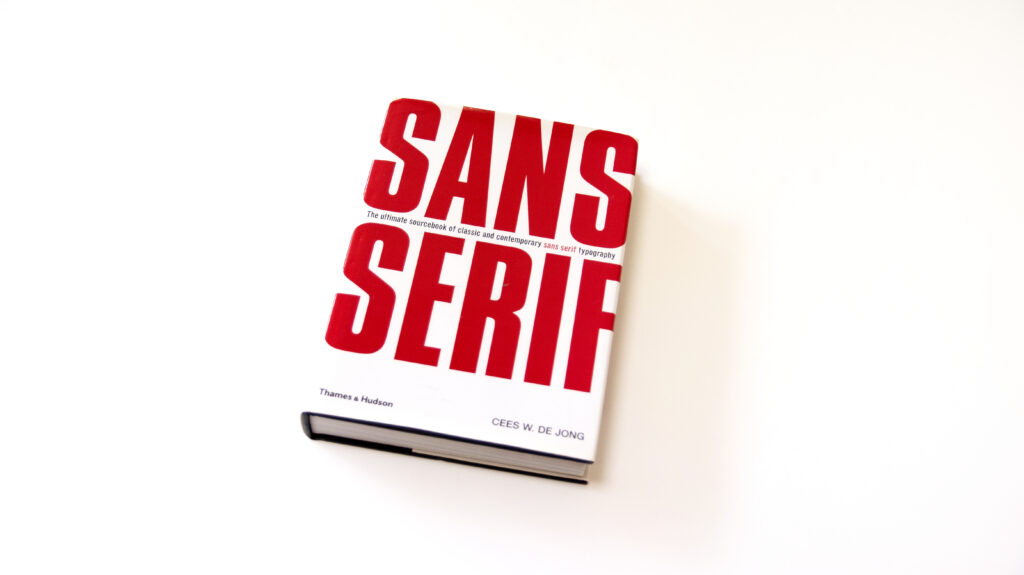
本書は1900年から2000年頃までの30種以上の主要なサンセリフを取り上げ、豊富な図版、解説とともに紹介しています。 サンセリフにだけに絞った書籍は珍しく、焦点を絞りやすいのが良いところです。また、時代に沿った構成になっており今も使われている書体はこの時代に生まれたのか、この時代にはこれが流行っていたのか、など様々な発見もあります。図版として単に眺めるだけでも楽しいですが解説も豊富なのでサンセリフについて勉強してみたいの方におすすめの一冊です。